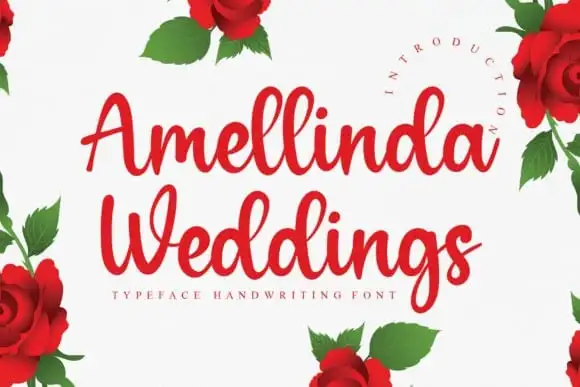
Amellinda Weddings Script Font – Fonte Grátis
Amellinda Weddings Script Font
Amellinda Weddings Script Font é uma elegante e delicada fonte feita especialmente para aqueles que buscam um toque autêntico em seus projetos. Desenvolvida pelo designer 99designs, lontong lodeh criou essa fonte que transmite a essência de uma letra escrita à mão. Ela é perfeitamente balanceada e tem caracteres de excelentes qualidades, tornando-a ideal para um amplo range de designs. Suas características belas e equilibradas permitem que ela combine perfeitamente com vários estilos de design, sejam elas convites de casamento, cartões de agradecimento, citações, cartões de felicitação, logotipos ou cartões de negócios. Nada faz melhor o seu projeto do que um toque único e autêntico, seja em um convite de casamento com uma mensagem delicada, em uma declaração de agradecimento para um convidado especial ou até mesmo em uma identidade visual que transmite sua personalidade única. Como você já pode imaginar, Amellinda Weddings Script Font faz essa tarefa suavemente e eficazmente. É perfeita para aqueles que desejam dar ao seu design um toque de delicadeza e elegância sem perder o encanto de uma letra escrita à mão.